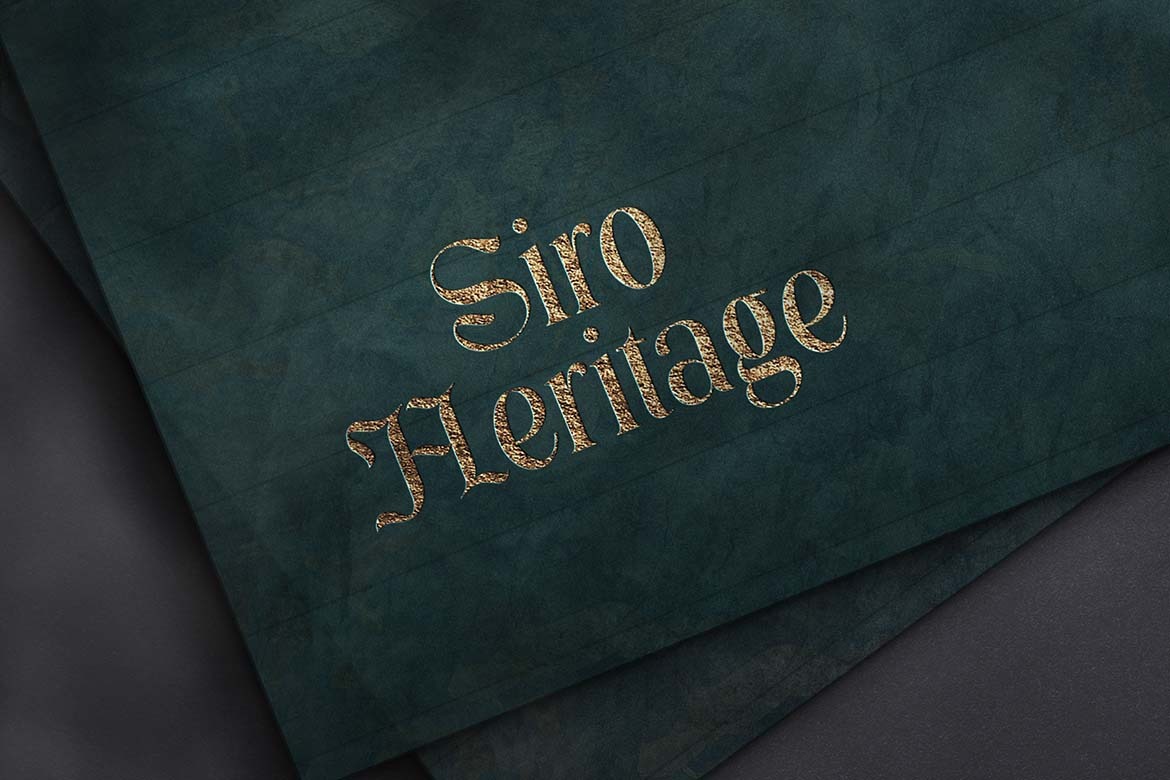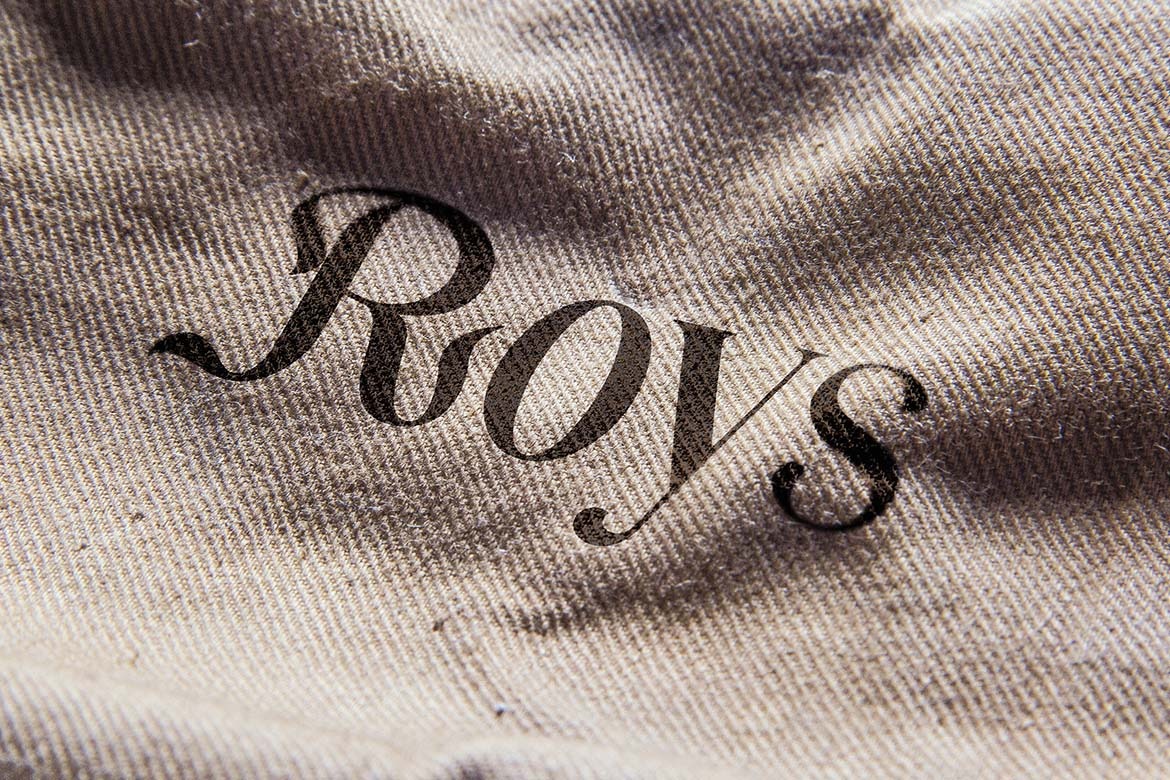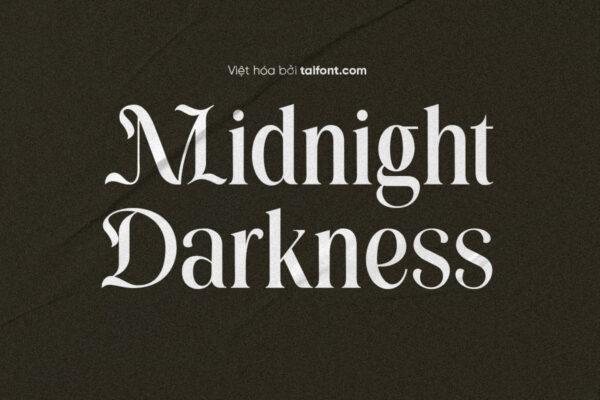
Font Việt hóa TF Midnight Darkness – Sự Sang Trọng Ẩn Mình Trong Đêm
Midnight Darkness là một phông chữ mang phong cách thanh lịch và huyền bí, kết hợp giữa sự mềm mại của nét viết tay và sự mạnh mẽ của chữ serif hiện đại. Với đường nét tinh xảo, độ dày vừa phải và những chi tiết uốn lượn đầy nghệ thuật, Midnight Darkness tạo cảm giác cao cấp, sang trọng và quyến rũ, giống như ánh sáng mờ ảo giữa màn đêm.
Ứng dụng của Midnight Darkness
Thiết kế thời trang: Phông chữ này rất phù hợp với các thương hiệu thời trang cao cấp, từ logo đến các ấn phẩm quảng bá. Nó giúp truyền tải sự tinh tế và đẳng cấp trong từng thiết kế.
Thương hiệu & Logo: Với vẻ đẹp thanh lịch và chuyên nghiệp, Midnight Darkness giúp logo và bộ nhận diện thương hiệu trở nên nổi bật, mang đến cảm giác uy tín và thời thượng.
Thiệp & Ấn phẩm nghệ thuật: Font chữ này lý tưởng cho các mẫu thiệp mời, thiệp cưới hay các thiết kế mang hơi hướng cổ điển và sang trọng. Những đường nét mềm mại nhưng đầy mạnh mẽ của Midnight Darkness giúp mỗi thông điệp trở nên ấn tượng hơn.
Nếu bạn đang tìm kiếm một font chữ vừa có sự thanh thoát, vừa toát lên vẻ đẹp quyền lực và lôi cuốn, Midnight Darkness chắc chắn là một lựa chọn không thể bỏ qua
Font Việt hóa TF Midnight Darkness